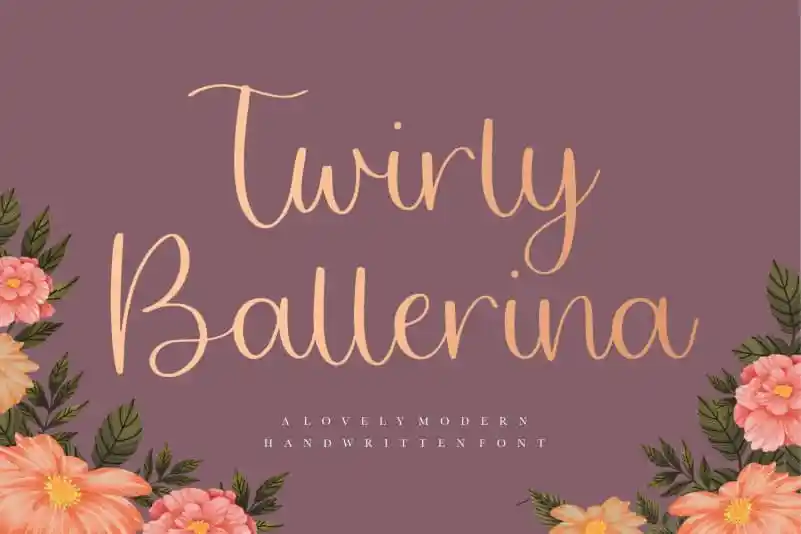
Twirly Ballerina Handwritten Font – Download Grátis
A Twirly Ballerina é uma fonte escrita à mão que oferece um toque encantador para qualquer projeto visual. Perfeita para aqueles projetos onde você deseja adicionar uma dose extra de romantismo e delicadeza, essa fonte ficará perfeitamente em sintonia com o seu próximo design de embalagem ou marca, revista ou mídia social. Além disso, é ideal para expressar os sentimentos acalentadores sobre um tema como casamento. O designer balpirick criou uma fonte à mão que não só captura a elegância e delicadeza típicos da dança de salão feminino, mas também incorpora o movimento em sua própria design. Essa característica torna cada letra fluida e envolvente, proporcionando um toque vivaz ao seu projeto. Tornará qualquer trabalho de marca ou embalagem mais convidativo e encantador. A Twirly Ballerina é uma escolha inteligente para aqueles projetos onde você deseja expressar emoções de forma suave e sofisticada, seja para criar um ambiente de relaxamento em sua próxima publicação ou para adicionar um toque elegante a um projeto de casamento. Com certeza, essa fonte é uma ótima opção para qualquer designer que procura tornar seus projetos mais criativos e atraentes.